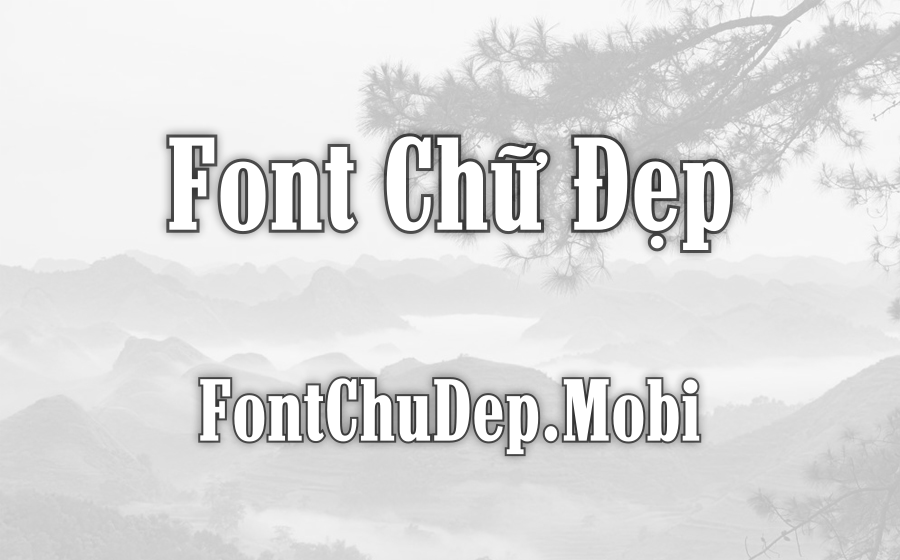
Font UTM Marlboro Việt Hóa
UTM Marlboro
UTM Marlboro chính là một font chữ mang đến hơi thở cổ điển của phương Tây mà bất kỳ ai yêu thích nét đẹp truyền thống không thể bỏ qua. Tôi đã có cơ hội trải nghiệm font chữ này và cảm thấy thực sự ấn tượng. Lấy cảm hứng từ typography nổi bật của các thương hiệu danh tiếng, UTM Marlboro tạo cho tôi cảm giác mạnh mẽ, nam tính và đồng thời cũng toát lên nét cá tính độc đáo. Đây chắc chắn là lựa chọn tuyệt vời cho những thiết kế cần sự thu hút và khác biệt.
Font chữ này đã được Việt hóa tỉ mỉ bởi Thiên Minh, điều này không chỉ giúp nó hỗ trợ hoàn hảo tiếng Việt mà còn mở rộng khả năng sử dụng với hơn 200 ngôn ngữ khác, đem lại sự linh hoạt tuyệt vời trong thiết kế. FontChuDep.mobi đã chăm chỉ sưu tầm và giới thiệu cho cộng đồng như một nguồn tài liệu giá trị, nhằm đáp ứng nhu cầu đa dạng của người dùng và hỗ trợ họ trong việc phát triển các dự án thực tế.
Đi sâu vào thiết kế, UTM Marlboro nổi bật với các nét chữ dày, sắc nét, thể hiện một chất vintage đầy cuốn hút. Font này thực sự thổi một làn gió mới vào các thiết kế như logo, biển hiệu, poster, bao bì sản phẩm và rất nhiều dự án sáng tạo khác. Tôi nhận thấy rằng nhiều ngành nghề như quảng cáo, ẩm thực, thiệp cưới và công nghệ đều có thể tận dụng triệt để UTM Marlboro để làm nổi bật các ấn phẩm của mình. Đây quả thật là một viên ngọc quý trong thế giới typographic.